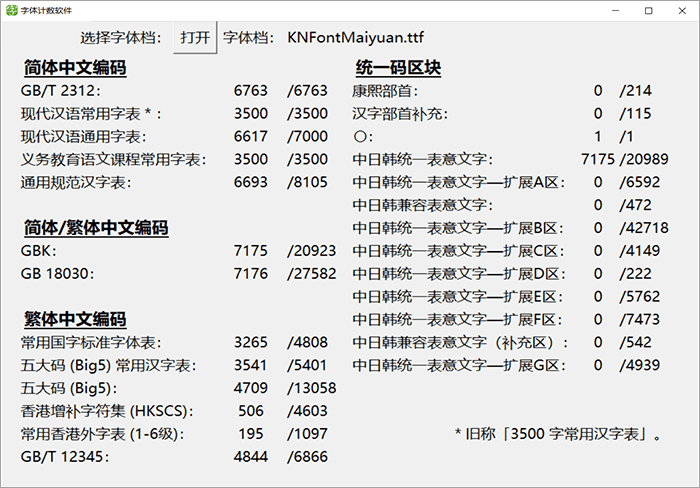
荆南麦圆体:荆南字坊力作 萌系可爱手写风格免费商用字体
不知道大家用荆南缘默体用得怎么样?用得爽不爽?告诉大家一个好消息,荆南缘默体的作者@荆南字坊又有新作啦!荆南麦圆体历经半年的肝夜紧张制作,终于发布测试版啦,其可爱的字型还是让人爱不惜手。
字体特点
荆南字坊麦圆体的设计灵感来源于韩国的一个综艺节目上的谚文字体,手写的风格圆润的笔画让这款字体看起来很可爱。
麦圆体萌系可爱的手写风格,字体每个笔画的粗细相同,两端圆润饱满,凸显可爱风格。虽是手写字体,笔画分明没有细小的连接,使字体更加清新俏皮。无论是做食品类还是母婴类,抑或是儿童类的设计都特别适合。
横画略偏斜,日字不封口,接近手写特征尾端圆润,横竖均一,保留趣味性的同时可读性高,也能适应屏幕显示。
你好,请问一下什么时候能把GB 18030-2022中缺失的汉字补充一下
2:如果没有混淆,请问我安装试用之后发现数字符号和西文的样式和字体样例中的不同,那么请问这是怎么回事呢?
真希望这款字体能把汉字补全
很好的一款字体,希望能把中文汉字补全。有时候偶然看见生僻字对于强迫症来说很割裂
Hey, I found a lightweighted version of this font!
为什么换了个这么Comic Sans的西文……
• 可能是Comic Neue(ofl字体),笔画比comic sans更直更平滑
1.2版本,又双叒叕,第三个ruo显示为桑葚的桑
那个,能不能把常用韩文2367个补一下,谢谢。原先下的韩文字体公司ruhua了。
请问,麦圆体能不能改成标准字间距啊,每次使用都需要手动调整字间距
“恃”字错显示为“恆”,“恆”字显示为一个奇怪的字,缺少摄氏度符号℃,期待修改
很喜欢,但是缺了摄氏度符号℃,繁体字“恆”也有错误,望修改
荆南麦圆体 v1.0 : (案) 字宝盖头上面一点太短,在小字号模式下,容易被误认为是 秃宝盖。建议后续版本调整优化。
“”双引号无法显示,直接空白,将空白设置成其它字体能正常显示出来
很可爱的字体,希望能把繁体字补全